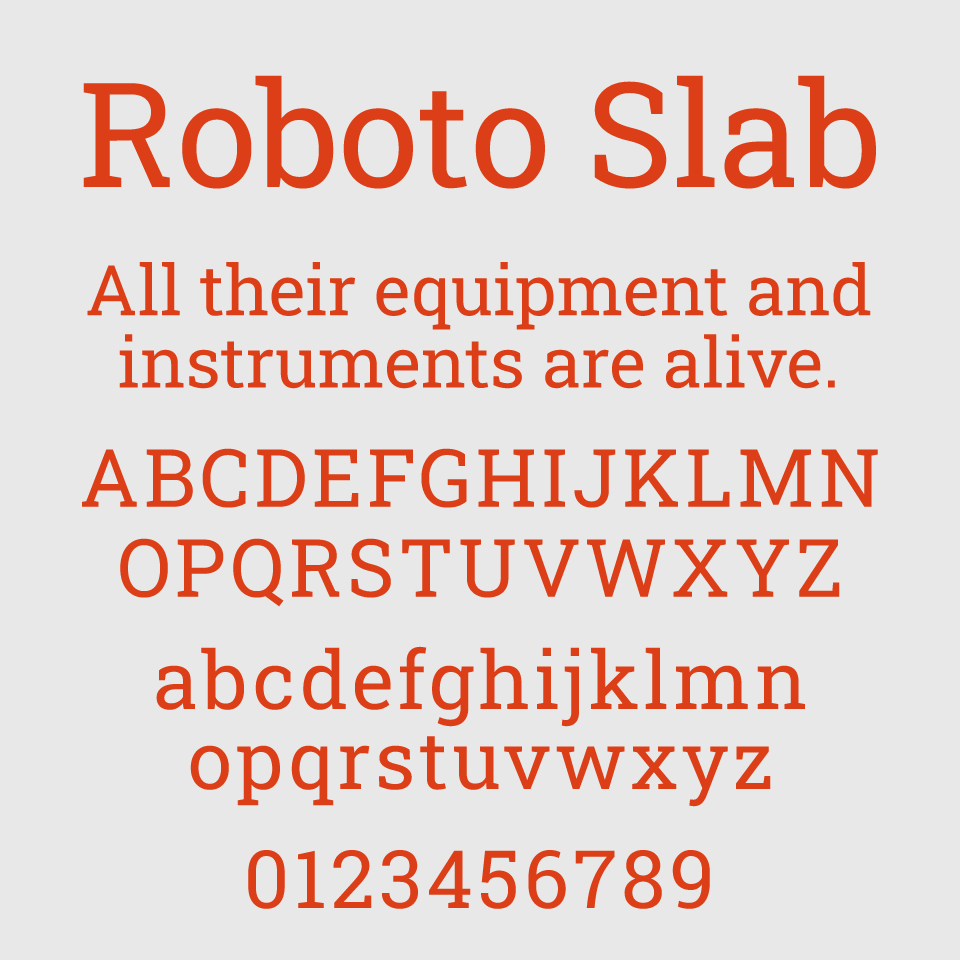
Roboto Slabフォントは、端正なフォルムとモダンな印象をもつ安定感のあるスラブセリフ体です。
線幅のコントラストが少なく、どっしりとした骨格が文字に信頼感と安心感があります。
デジタルメディアや企業サイトなど、堅実さを求められるシーンで特に効果を発揮するフォントです。クラシカルなセリフ体の風格を残しつつ、現代的に洗練されたバランスで、ビジネス用途にも馴染みやすいフォントです。